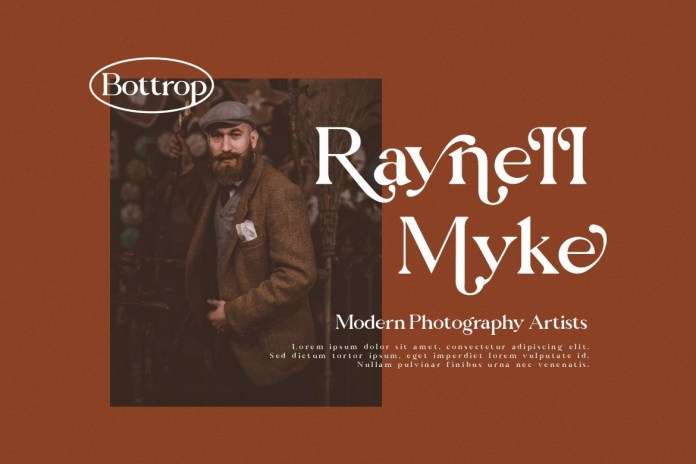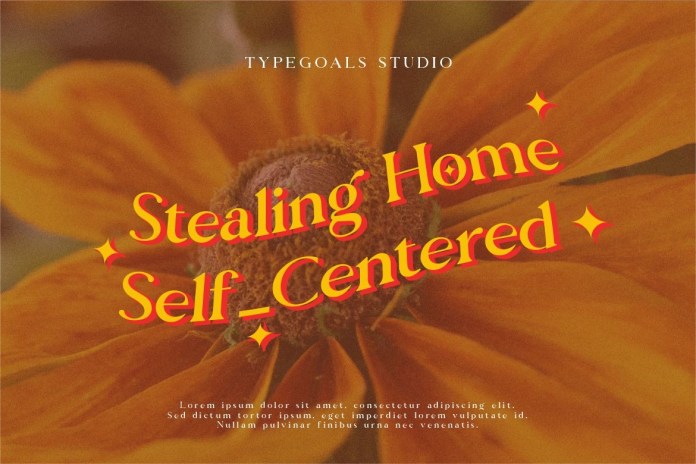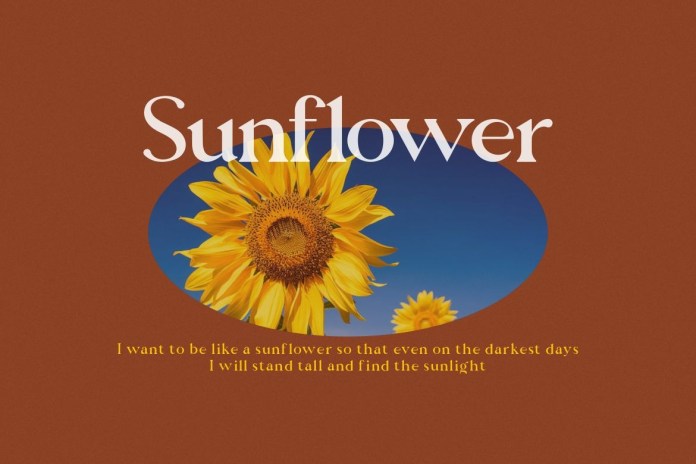
Dalgona Candy 字体下载,这款字体结构工整、笔画清晰,兼顾美观与易读性,适用于标题、正文、海报、包装、LOGO 等多种场景。字形优雅稳定,风格百搭耐看,适配日常排版与创意设计,让文字呈现更舒适、更具质感。Dalgona Candy 字体下载一笔一画,皆是细节,以均衡的比例、流畅的线条打造舒适视觉体验,字形端正大气,风格简约现代。无论是商业设计、品牌宣传还是日常排版,都能轻松驾驭,让文字更有格调与力量。Dalgona Candy 字体下载字体下载。
Dalgona Candy Serif 字体介绍
This font is a modern multilingual serif enhanced by ligatures & alternates. It’s designed and shared by Typegoals Studio. This typeface is perfect for an elegant & luxury logo, book or movie title design, fashion brand, magazine, clothes, lettering, quotes, and so much more.